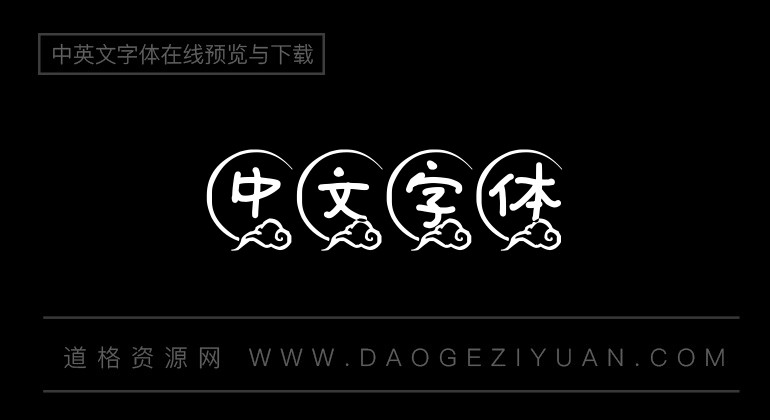
默陌歪歪体中秋版是一款圆润、清新、活泼的中文字体,以中秋节为主题,融入了中秋节的元素,让文字更加具有节日气息。字体的曲线简洁优美,笔画流畅自然,给人以清新可爱的感觉,是一款适合把祝福传达给朋友的字体。文件名:MoMoWaiWaiTiZhongQiuBan-2.ttf
默陌歪歪体中秋版是一款非常不错的手写艺术字体,具有很好的视觉感,适合于文化类的宣传设计、商业类品牌的广告和产品包装设计以及个性化文字排版等较多场景。